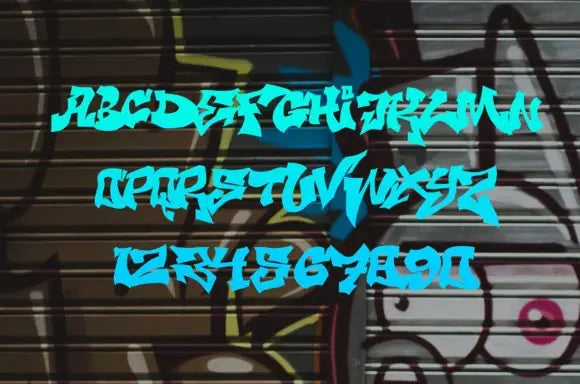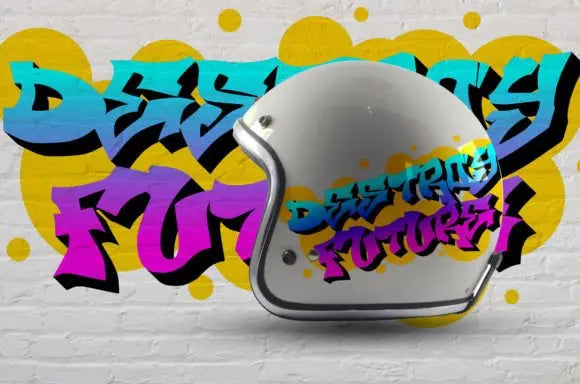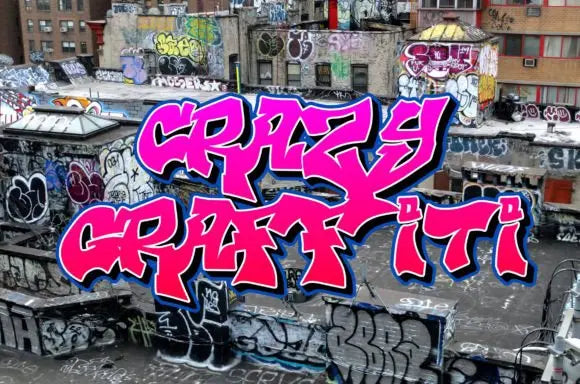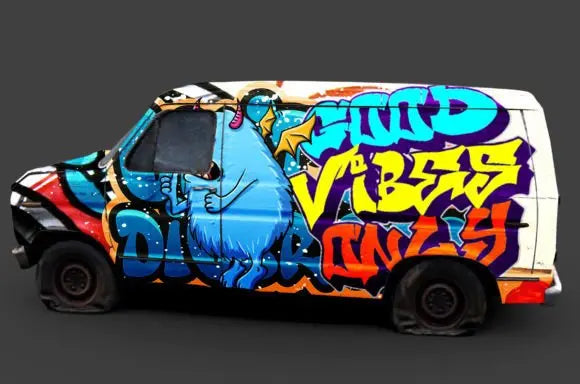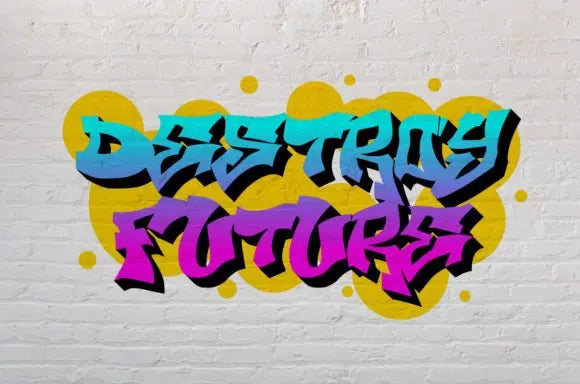
Fuente Big King
Big King es una fuente de visualización espectacular con caracteres gruesos y grasosos estilo graffiti. Elevará una amplia gama de proyectos de diseño al más alto nivel, ya sea marcas, encabezados, diseños de bodas, invitaciones, firmas, logotipos, ilustraciones de arte mural, indumentaria, etiquetas y mucho más.